싸인은 복잡할수록 멋있다고 생각할 수 있지만, 오히려 단순한 싸인이 더 세련되고 강렬한 인상을 줄 수 있어요. 특히 빠르게 쓰면서도 개성을 유지할 수 있는 싸인이 가장 실용적이고 멋진 싸인이 될 수 있어요. ✍🔥
내가 생각했을 때, 단순하지만 멋진 싸인을 만들려면 몇 가지 핵심 원칙을 따르면 돼요. 이제 단순하면서도 멋진 싸인을 만드는 핵심 요소를 알아볼까요? 🚀
단순한 싸인이 멋진 이유 🔥
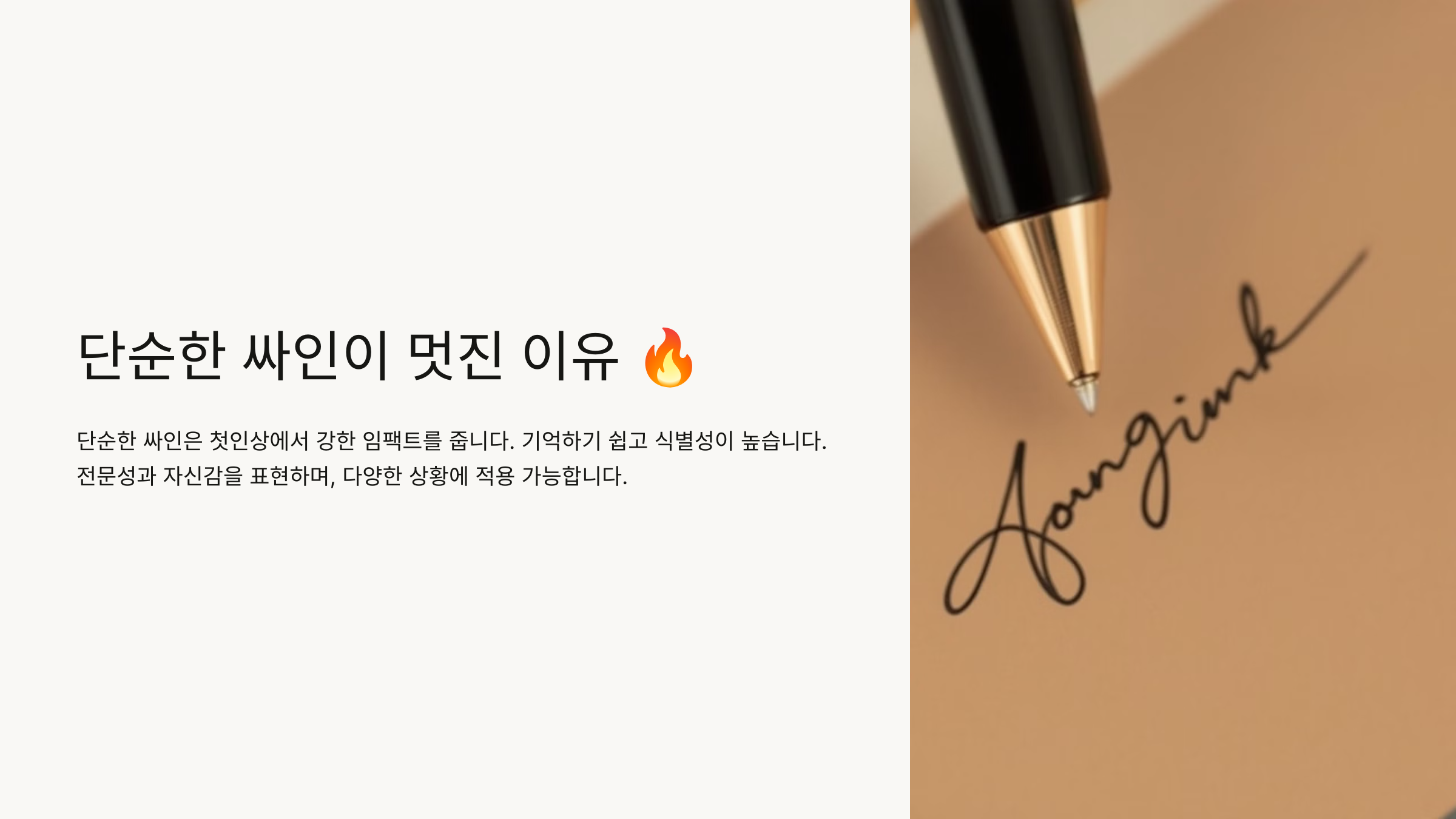
싸인은 단순할수록 빠르고 일관되게 작성할 수 있어요. 너무 복잡한 싸인은 실용성이 떨어지고, 매번 다른 형태로 변할 수도 있어요. ✍🔥
🔹 단순한 싸인이 멋진 이유
✔ 빠르게 쓸 수 있어 실용적
✔ 한 번 보면 기억하기 쉬움
✔ 공식 문서에서도 일관성 유지 가능
✔ 가독성이 좋아 어디서든 활용 가능
📌 단순한 싸인의 장점 ✨
장점 설명 속도 복잡한 싸인보다 빠르게 작성 가능 기억하기 쉬움 단순할수록 인지하기 쉬움 일관성 언제 어디서든 같은 싸인을 유지 가능 가독성 어디서든 쉽게 알아볼 수 있음 이제 싸인을 단순하게 만드는 핵심 요소를 살펴볼까요? ✅
싸인을 단순하게 만드는 핵심 요소 ✅
멋진 싸인을 만들기 위해서는 불필요한 요소를 줄이고 핵심을 강조하는 것이 중요해요. 획을 간결하게 정리하고, 빠르고 쉽게 쓸 수 있도록 디자인해야 해요. ✍🔥
🔹 단순한 싸인을 만드는 핵심 요소
✔ 이니셜을 강조해 짧고 강렬한 디자인 만들기
✔ 불필요한 곡선과 장식 줄이기
✔ 획을 연결해 부드러운 흐름 만들기
✔ 크기와 비율을 조절해 균형 있는 디자인 유지
📌 단순한 싸인을 만드는 핵심 요소 ✨
핵심 요소 설명 이니셜 강조 이름의 첫 글자만 사용해 짧고 강렬한 싸인 장식 제거 불필요한 곡선과 복잡한 장식 줄이기 획 연결 부드럽고 자연스럽게 이어지는 흐름 만들기 비율 조절 균형 잡힌 크기로 가독성을 높이기 이제 획과 공간을 활용하는 방법을 살펴볼까요? 🎨
획과 공간을 활용하는 방법 🎨
싸인을 단순하지만 멋지게 만들기 위해서는 획과 공간의 활용이 중요해요. 획을 어떻게 배치하고, 여백을 얼마나 둘지에 따라 싸인의 균형과 가독성이 달라질 수 있어요. ✍🔥
🔹 획과 공간을 활용하는 핵심 원칙
✔ 불필요한 획을 줄이고 핵심만 남기기
✔ 획을 길게 빼거나 강조해서 개성을 살리기
✔ 균형 잡힌 여백으로 싸인을 정돈된 느낌으로 만들기
✔ 획의 시작과 끝을 명확하게 하여 가독성 높이기
📌 획과 공간을 활용하는 팁 ✨
방법 설명 불필요한 획 줄이기 꼭 필요한 선만 남기고 간결한 디자인 유지 획 강조 획을 길게 빼거나 강하게 눌러 개성 추가 균형 잡힌 여백 글자 간격을 일정하게 조절해 가독성 확보 획의 시작과 끝 명확히 흐릿하거나 어색한 마무리를 방지하여 완성도 높이기 이제 이니셜을 강조하는 효과적인 방법을 살펴볼까요? 🔠
이니셜을 강조하는 효과적인 방법 🔠
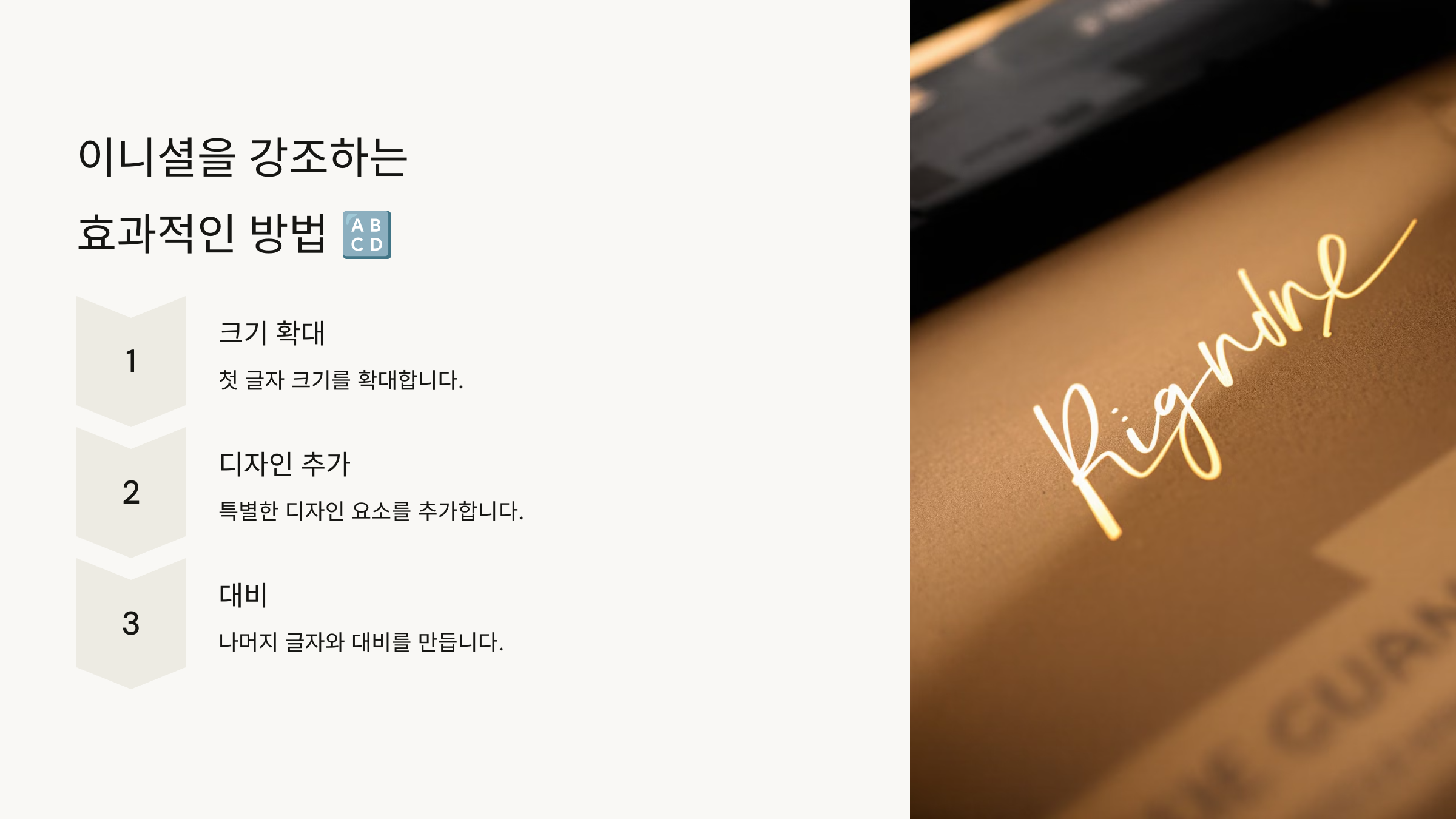
이니셜을 강조하면 싸인을 더 짧고 간결하게 만들 수 있어요. 특히 이름 전체를 쓰기 어려운 경우 이니셜만 활용해도 충분히 개성 있는 싸인을 만들 수 있어요. ✍🔥
🔹 이니셜을 강조하는 핵심 포인트
✔ 대문자로 강한 인상 남기기
✔ 이니셜을 기울여 다이내믹한 느낌 연출
✔ 획을 길게 빼서 스타일 강조
✔ 이니셜과 곡선을 조합해 부드러운 흐름 만들기
📌 이니셜을 강조하는 싸인 스타일 ✨
스타일 설명 느낌 대문자 강조 이니셜을 대문자로 작성해 강한 인상 남기기 힘 있고 단단한 느낌 기울임 효과 이니셜을 약간 기울여 독특한 디자인 유니크하고 감각적인 스타일 획 길게 빼기 이니셜 마지막 획을 길게 늘려 멋스럽게 표현 우아하고 세련된 느낌 곡선 조합 이니셜과 부드러운 곡선을 조합해 자연스러운 흐름 부드럽고 감성적인 스타일 이제 자연스러운 흐름을 위한 필기법을 살펴볼까요? ✍
자연스러운 흐름을 위한 필기법 ✍
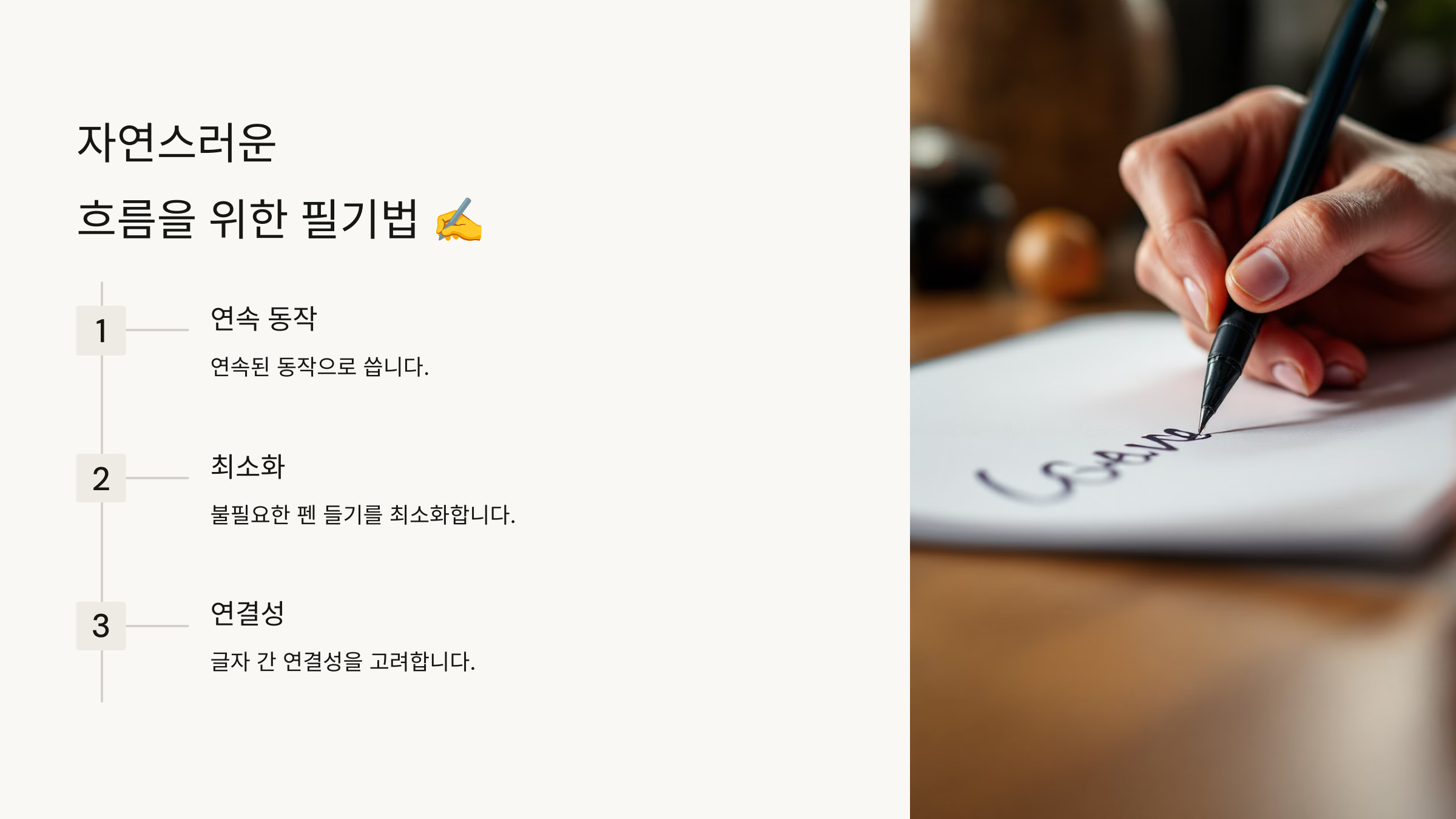
싸인은 자연스럽게 흘러가듯 써야 멋진 스타일이 완성돼요. 글씨를 억지로 꾸미려 하면 오히려 부자연스러워질 수 있기 때문에, 손에 익는 필기법을 익혀 자연스러운 흐름을 만드는 것이 중요해요. ✍🔥
🔹 자연스러운 흐름을 위한 필기법
✔ 연결되는 획을 활용해 부드러운 곡선 만들기
✔ 손목의 힘을 빼고 가볍게 써보기
✔ 처음과 끝을 매끄럽게 이어주는 연습하기
✔ 빠른 속도로 연습하여 싸인을 손에 익히기
📌 자연스럽고 멋진 싸인을 위한 필기법 ✨
필기법 설명 효과 연결되는 획 활용 끊김 없이 자연스럽게 이어지는 필기법 부드럽고 우아한 싸인 연출 손목의 힘 빼기 필기할 때 손에 힘을 빼고 자연스럽게 움직이기 자연스럽고 편안한 싸인 완성 처음과 끝을 부드럽게 시작과 끝을 날렵하게 정리해 세련된 느낌 연출 깔끔하고 정리된 싸인 빠른 속도로 연습 여러 번 반복하여 빠르게 싸인하는 연습 실제 문서에서도 빠르게 활용 가능 이제 단순하면서도 개성 있는 싸인 스타일 추천을 살펴볼까요? 🌟
단순하면서도 개성 있는 싸인 스타일 추천 🌟
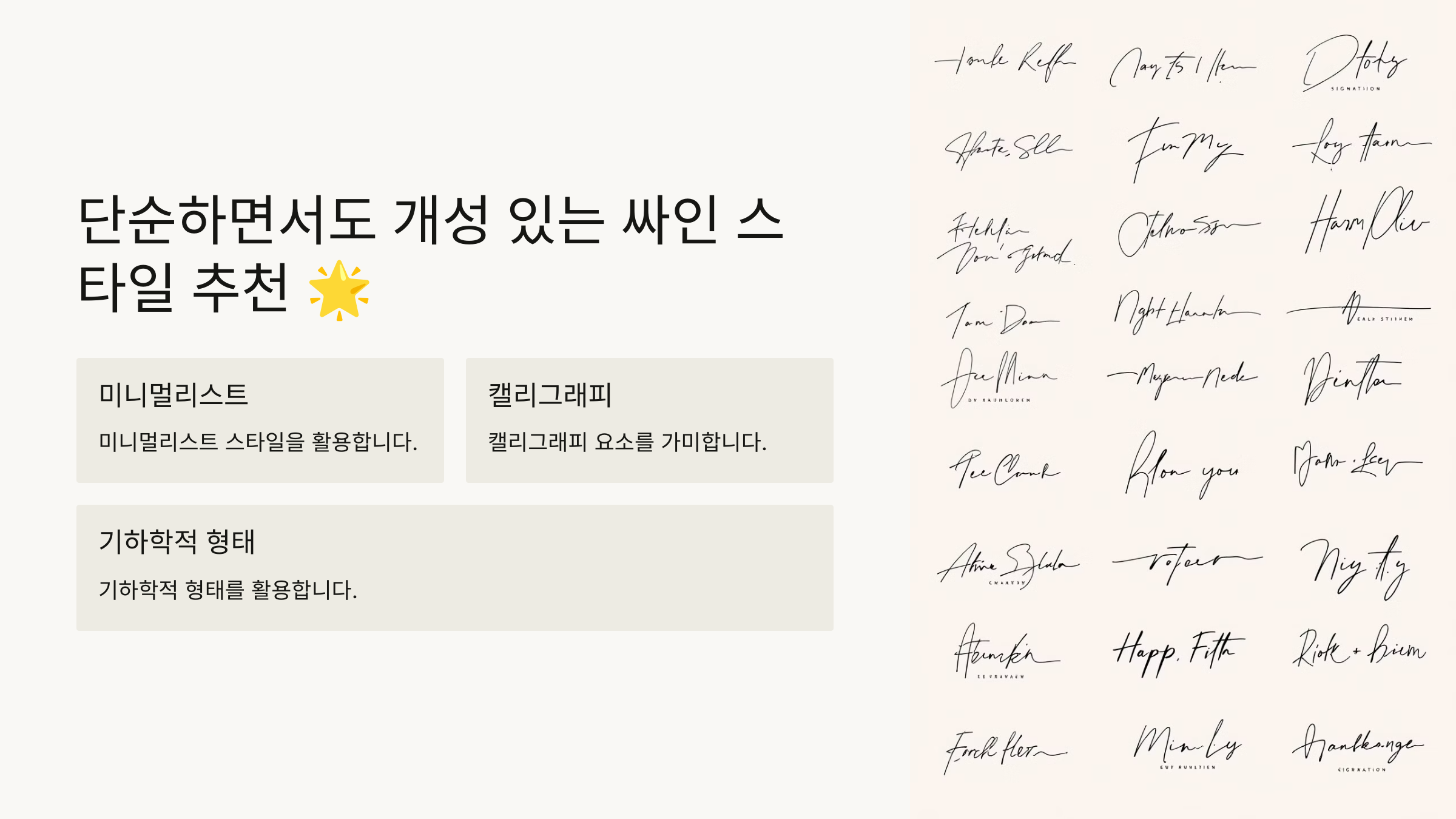
단순하지만 멋진 싸인을 만들려면 불필요한 장식을 줄이면서도 개성을 살려야 해요. 한 번 보면 기억에 남을 수 있도록 자신만의 스타일을 반영하는 것이 중요해요! ✍🔥
🔹 개성 있는 싸인을 위한 스타일 추천
✔ 곡선 활용 스타일 – 부드럽고 감성적인 느낌
✔ 직선 강조 스타일 – 강렬하고 세련된 인상
✔ 이니셜 조합 스타일 – 짧고 간결하면서도 강렬한 디자인
✔ 기호(⭐, ✔, _) 활용 스타일 – 차별화된 개성 연출
📌 개성 있는 싸인 스타일 추천 ✨
스타일 특징 느낌 곡선 활용 부드러운 곡선을 강조해 자연스러운 흐름 연출 우아하고 감성적인 스타일 직선 강조 강한 직선을 활용해 힘 있고 단단한 느낌 세련되고 강렬한 인상 이니셜 조합 이름의 첫 글자를 조합해 간결하게 디자인 짧고 기억하기 쉬운 스타일 기호 활용 ⭐, ✔, _ 등의 기호를 추가해 포인트 연출 독창적이고 차별화된 개성 이제 싸인과 관련된 궁금증을 해결할 시간! FAQ에서 자주 묻는 질문을 살펴볼까요? ❓
FAQ ❓
Q1. 싸인을 만들 때 가장 중요한 요소는 무엇인가요?
A1. 싸인을 만들 때 중요한 요소는 간결함, 개성, 가독성이에요. ✔ 빠르게 쓸 수 있도록 복잡한 장식을 줄이기 ✔ 한눈에 알아볼 수 있도록 균형 있는 디자인 유지 ✔ 자신만의 스타일을 반영하여 개성 있는 싸인 만들기
Q2. 싸인을 계속 바꿔도 괜찮을까요?
A2. 개인적인 싸인은 바꿔도 괜찮지만, 공식 문서에서 사용하는 싸인은 일관성을 유지해야 해요. ✔ 은행, 공공기관 등에 등록된 싸인은 변경 시 다시 등록 필요 ✔ 새로운 싸인을 충분히 연습한 후 적용하는 것이 안전
Q3. 싸인에 기호(⭐, ✔, •)를 추가해도 될까요?
A3. 기호를 활용하면 싸인의 개성을 더할 수 있어요. ✔ 별(⭐), 점(•), 밑줄(━) 등을 활용해 포인트 주기 ✔ 너무 많은 장식은 가독성을 떨어뜨릴 수 있으므로 적절하게 사용하기
Q4. 싸인의 크기는 어떻게 조절하는 것이 좋을까요?
A4. 문서에 맞게 크기를 조절하는 것이 좋아요. ✔ 공식 문서, 계약서에서는 작은 크기로 깔끔하게 작성 ✔ 팬 사인회, 명판 등에서는 크고 인상적으로 작성
Q5. 싸인을 빠르게 쓰는 연습법이 있나요?
A5. 싸인을 빠르게 쓰려면 반복 연습과 자연스러운 흐름을 익히는 것이 중요해요. ✔ 하루 5~10분씩 반복 연습하기 ✔ 손목의 힘을 빼고 가볍게 써보기 ✔ 이니셜을 활용해 간결하면서도 직관적인 싸인 만들기
Q6. 전자 서명과 수기 싸인을 동일하게 만들 수 있나요?
A6. 태블릿이나 스타일러스 펜을 활용하면 디지털과 수기 싸인의 일관성을 유지할 수 있어요. ✔ Adobe Sign, DocuSign 같은 전자 서명 도구 활용 ✔ PNG 파일로 저장하여 문서에 삽입 가능 ✔ 종이에 연습한 싸인을 디지털에서도 동일하게 재현
Q7. 싸인을 더 세련되게 바꾸는 방법이 있나요?
A7. 싸인을 세련되게 만들려면 불필요한 요소를 제거하고 핵심을 강조하는 것이 중요해요. ✔ 이니셜을 활용해 간결하고 강렬한 스타일로 변경 ✔ 곡선과 직선을 적절히 조합해 균형 있는 디자인 만들기 ✔ 불필요한 획을 줄이고 자연스러운 흐름 유지
Q8. 한글 싸인과 영어 싸인 중 어떤 것이 더 좋을까요?
A8. 한글과 영어 중 어떤 걸 사용할지는 본인의 스타일과 용도에 따라 선택하면 돼요. ✔ 한글 싸인 – 독창적이고 한국적인 느낌 강조 ✔ 영어 싸인 – 글로벌하게 활용 가능하고 세련된 느낌 ✔ 한글+영어 조합 – 성(姓)은 한글, 이름은 영어 등 독특한 스타일 가능
이제 싸인을 단순하면서도 멋지게 만드는 핵심 원칙을 완벽하게 배웠어요! 🎯 꾸준히 연습해서 자신만의 개성 있는 싸인을 완성해 보세요! ✍🔥